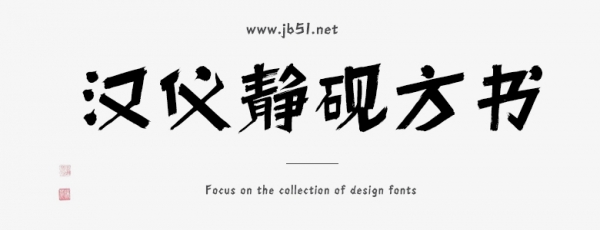
漢儀靜硯方書(shū)W是由漢儀字庫(kù)出品,字體筆觸適中,書(shū)寫流暢,具有很好的視覺(jué)感,適合應(yīng)用于藝術(shù)設(shè)計(jì)、平面宣傳設(shè)計(jì)、網(wǎng)頁(yè)設(shè)計(jì),書(shū)法字帖等領(lǐng)域,需要的朋友可以前來(lái)本站下載。